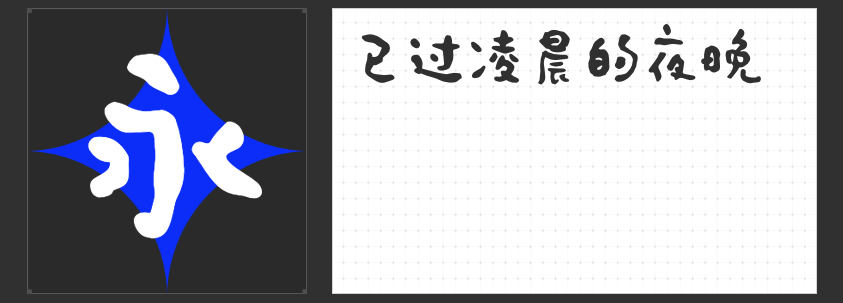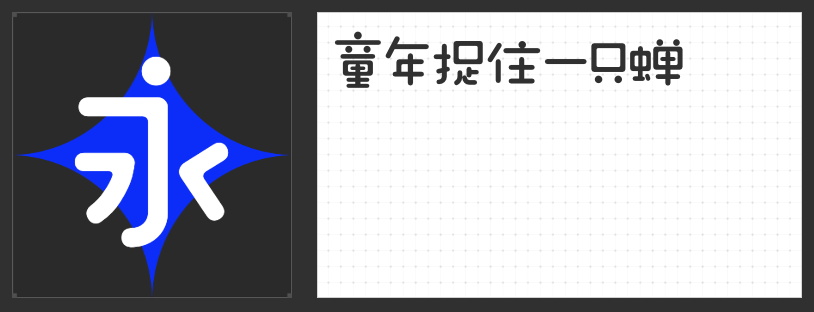
~设计中不可或缺的简体繁体兼备字体推荐~
在设计的世界里,字体选择至关重要,它不仅能传达信息,更能营造氛围、引导情绪。今天,为大家推荐四款既适用于简体又兼容繁体的优秀字体,它们各具特色,能在各类设计项目中大放异彩。
一、励字综艺简繁:严谨中的活泼艺术
“励字综艺简繁”以其粗犷而不失规矩的笔触,完美融合了活泼与严谨。笔画粗壮,横平竖直,空间利用极致,拐弯处圆润方正,展现出极强的艺术性。这种字体适合用于需要强调力量感、现代感的设计作品,如海报、广告标题等,能迅速吸引目光,留下深刻印象。
二、励字造桃气圆 常规:圆润中的灵动变化
“励字造桃气圆 常规”则是一款以手写感为灵魂的圆体字,字形上松下紧,圆润饱满,变化多端。其独特的断开笔画设计,赋予了字体轻快的特质,使得整体风格既温馨又不失活泼。这款字体适合用于邀请函、儿童读物封面等,能营造出温馨、亲切的氛围。
三、字恋狂澄空 絮风:手写韵律的灵动演绎
“字恋狂澄空 絮风”同样基于手写感,但其结构更加灵活多变,字面随字形自然调整,展现出极高的设计自由度。字间距的合理安排,让文字组合起来如一首流动的诗,富有节奏感。这款字体适合用于诗歌集、艺术展览海报等,能够完美诠释作品的内在韵律。
四、字恋狂深夜简繁:创意手写的自由不羁
最后,“字恋狂深夜简繁”以其如同流水般蜿蜒的笔触,字形散漫扭曲,带来一种超脱常规的美感。这种字体仿佛带着夜晚的神秘与自由,适合用于创意广告、音乐专辑封面等,能够激发观众无限遐想,传递出与众不同的品牌个性。
这四款字体,无论是追求严谨艺术、温馨圆润、灵动韵律还是自由不羁,都能在设计中找到它们的一席之地,为你的作品增添无限魅力。